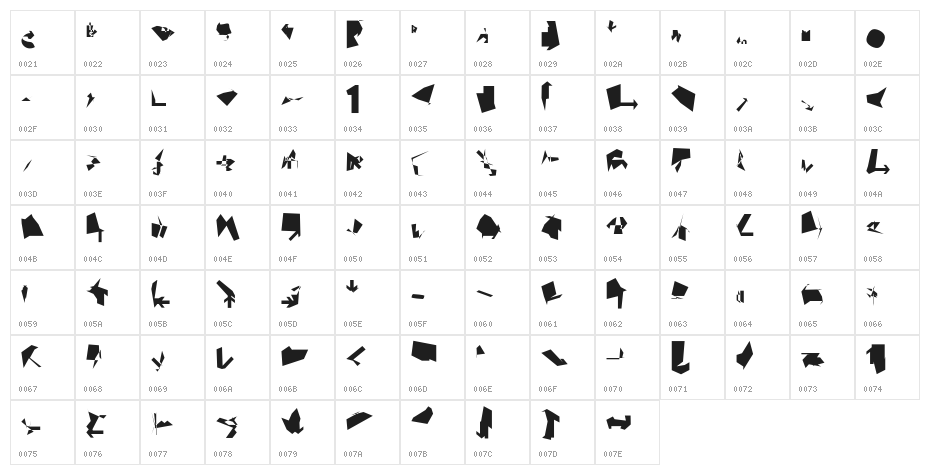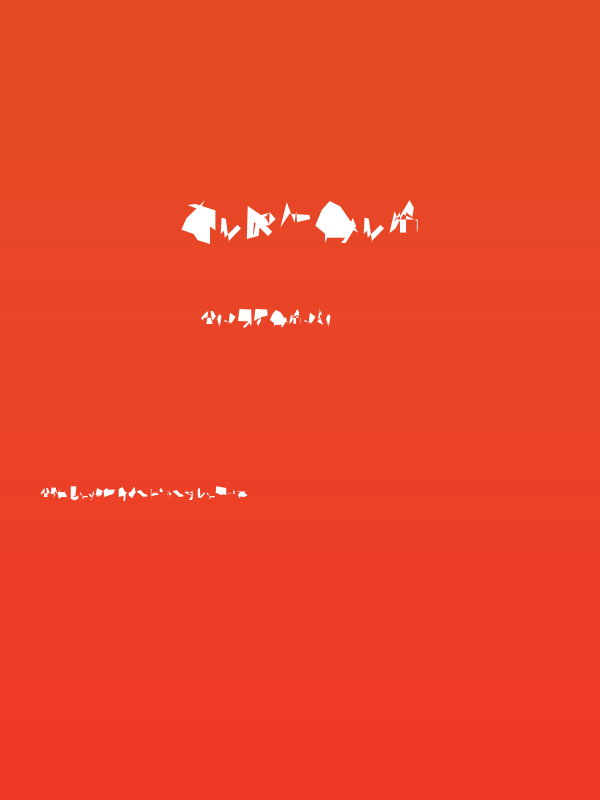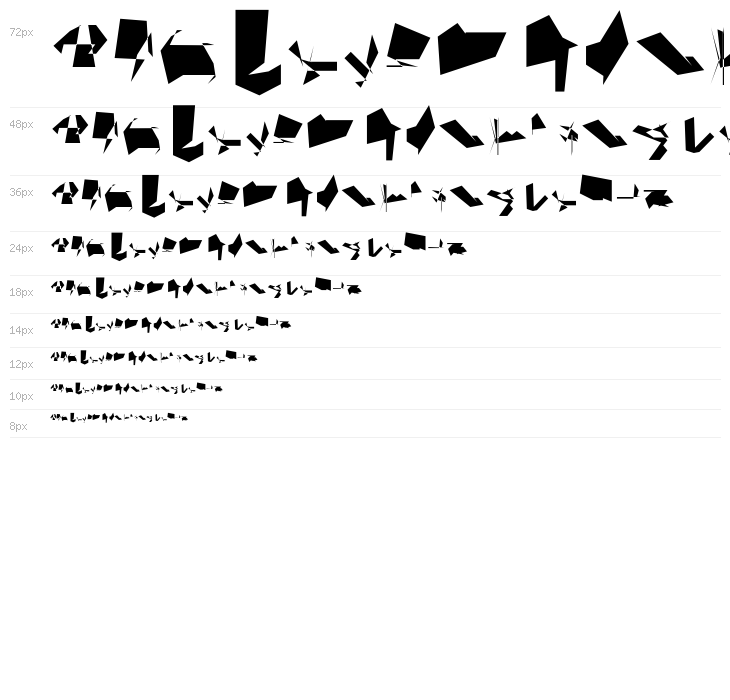
Siberia Font
| Estilo general | Avant-garde, Experimental |
| Caso de uso | Logos, Artistic displays, Creative branding |
| Proyectos propuestos | Ideal for avant-garde art projects, experimental design work, and creative branding that seeks to make a bold statement. |